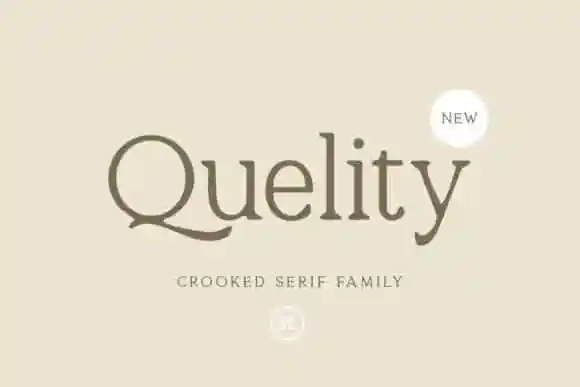
A Quelity Serif Font é uma escolha incrível para quem busca a combinação perfeita entre modernidade e nostalgia. Esta elegante tipografia serif oferece 16 faces, incluindo linhas leves e negritos com itálico em cada estilo. Perfeito tanto para criar logos e estilos clássicos quanto para textos legíveis e profissionais, esta família de fontes suporta idiomas multilíngues, números e símbolos. Se você está cansado dos serifados mais convencionais, a Quelity Serif pode ser justamente o que procura para dar um toque único aos seus projetos. Não perca tempo – essa é uma fonte certamente capaz de fazer sua marca brilhar em qualquer projeto.